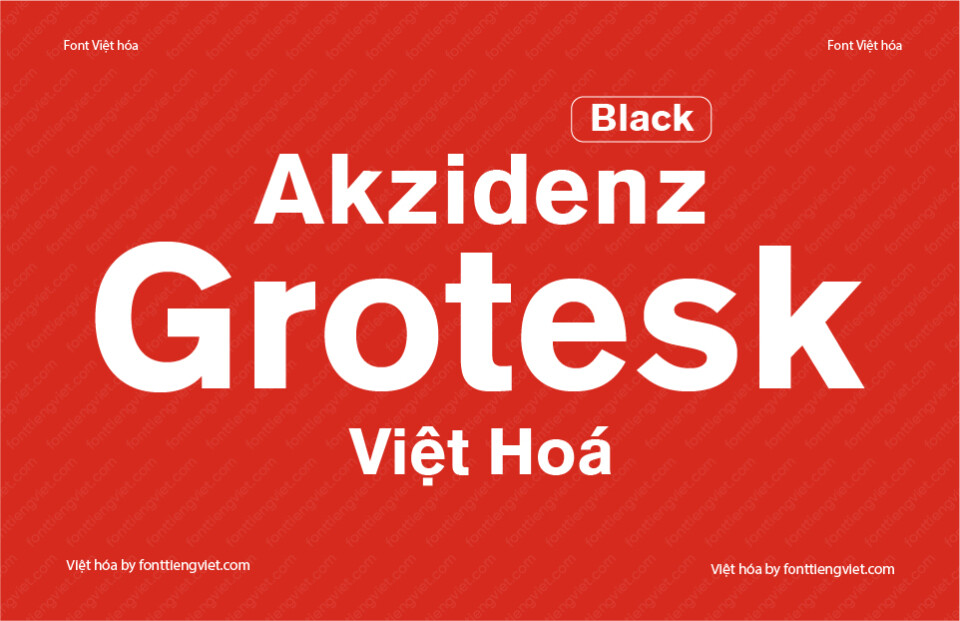
Font Việt hóa 1FTV VIP Akzidenz Grotesk Black
Font Việt hóa 1FTV VIP Akzidenz Grotesk Black – Sự Lựa Chọn Hoàn Hảo Cho Thiết Kế Ấn Tượng
Tìm hiểu về Font Việt hóa 1FTV VIP Akzidenz Grotesk Black trong thiết kế hiện đại
Trong thế giới đồ họa chuyên nghiệp, việc lựa chọn một Font Miễn Phí chất lượng luôn là ưu tiên hàng đầu của các nhà thiết kế. Đặc biệt, Font Việt hóa 1FTV VIP Akzidenz Grotesk Black nổi lên như một biểu tượng của sự mạnh mẽ, quyết đoán và hiện đại. Đây là phiên bản được tinh chỉnh kỹ lưỡng, hỗ trợ đầy đủ bộ gõ tiếng Việt, giúp loại bỏ hoàn toàn các lỗi hiển thị dấu phổ biến. Với độ dày nét chữ (weight) cực lớn, font chữ này không chỉ mang lại cảm giác chắc chắn mà còn tạo ra sự uy tín cho các thông điệp truyền tải. Trong môi trường học đường hay các dự án giáo dục, việc sử dụng phông chữ chuẩn xác giúp học sinh dễ dàng tiếp cận thông tin một cách trực quan và sinh động nhất.
Lịch sử và phong cách của dòng Akzidenz Grotesk
Akzidenz Grotesk vốn là nguồn cảm hứng cho nhiều bộ chữ nổi tiếng sau này như Helvetica hay Univers. Khi được chuyển hóa sang phiên bản Font Việt hóa 1FTV VIP Akzidenz Grotesk Black, nó vẫn giữ nguyên được tinh thần cổ điển của trường phái Bauhaus nhưng lại pha chút hơi thở đương đại. Các nét chữ được thiết kế tối giản, loại bỏ những chi tiết thừa thãi để tập trung vào sự rõ ràng. Điều này cực kỳ quan trọng đối với các bạn học sinh đang làm quen với thiết kế slide thuyết trình hoặc báo tường, nơi mà sự mạch lạc trong trình bày văn bản luôn được đề cao hàng đầu.
Tại sao nên sử dụng Font Việt hóa 1FTV VIP Akzidenz Grotesk Black cho các dự án sáng tạo?
Sự khác biệt lớn nhất của Font Việt hóa 1FTV VIP Akzidenz Grotesk Black nằm ở khả năng ứng dụng đa dạng. Dù bạn đang thực hiện một poster sự kiện nhà trường hay thiết kế bìa sách giáo khoa, bộ font này luôn đảm bảo tính thẩm mỹ cao. Nhờ vào cấu trúc Sans-serif (không chân) đặc trưng, các ký tự trở nên dễ đọc hơn ngay cả khi quan sát từ khoảng cách xa. Hơn nữa, phiên bản VIP này đã được tối ưu hóa về khoảng cách giữa các chữ cái (kerning), giúp văn bản trông hài hòa và chuyên nghiệp hơn bao giờ hết.
Ứng dụng thực tế trong học tập và giảng dạy
Đối với giáo viên và học sinh, việc sử dụng Font Việt hóa 1FTV VIP Akzidenz Grotesk Black giúp các bài giảng điện tử trở nên cuốn hút hơn. Thay vì sử dụng những phông chữ quá quen thuộc và nhàm chán, việc thay đổi sang một bộ font đậm nét và hiện đại sẽ giúp nhấn mạnh vào các tiêu đề quan trọng, từ đó giúp người xem dễ dàng ghi nhớ kiến thức. Sự chắc chắn trong từng đường nét của font chữ này cũng tượng trưng cho tính chính xác và khoa học, rất phù hợp cho các môn học tự nhiên hay các tài liệu hướng dẫn kỹ thuật cơ bản.
Việc cài đặt bộ font này vô cùng đơn giản trên cả hệ điều hành Windows và macOS. Sau khi tải về, bạn chỉ cần giải nén và nhấn cài đặt để hệ thống tự động nhận diện. Tuy nhiên, để phát huy tối đa vẻ đẹp của Font Việt hóa 1FTV VIP Akzidenz Grotesk Black, bạn nên sử dụng nó cho các tiêu đề lớn (Headings) thay vì các đoạn văn bản dài. Sự tương phản giữa một tiêu đề đậm nét và phần nội dung mảnh mai sẽ tạo ra một phân cấp thị giác rõ rệt, giúp người xem không bị rối mắt. Đây là một quy tắc thiết kế cơ bản mà bất kỳ ai cũng có thể áp dụng để nâng tầm tác phẩm của mình.
Kết luận về giá trị của bộ font đặc biệt này
Tóm lại, việc sở hữu một bộ phông chữ chất lượng như Font Việt hóa 1FTV VIP Akzidenz Grotesk Black là bước đi đúng đắn cho bất kỳ ai muốn nâng cao tính thẩm mỹ cho sản phẩm của mình. Không chỉ đáp ứng tốt về mặt kỹ thuật việt hóa, nó còn mang lại giá trị cảm xúc mạnh mẽ thông qua từng đường nét thiết kế. Hãy bắt đầu trải nghiệm và khám phá thế giới sáng tạo cùng Font Miễn Phí, Font Việt Hóa, Font Việt hóa 1FTV VIP Akzidenz Grotesk Black ngay hôm nay để thấy được sự khác biệt vượt trội trong mỗi bản thiết kế của bạn.